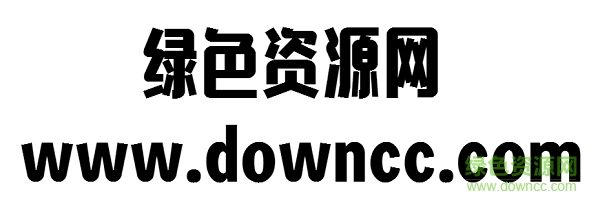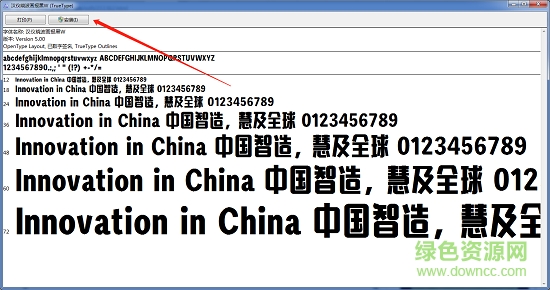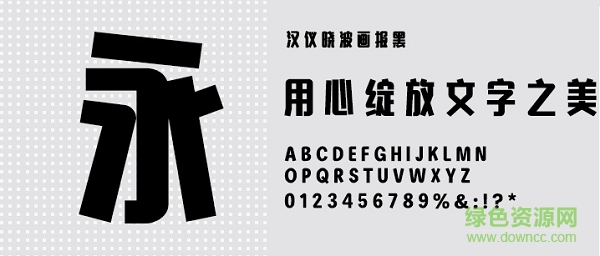
漢儀曉波畫報黑W(漢儀曉波藝術(shù)字體)是一款非常不錯的整體上瘦長的漢儀字體,正如其名畫報體,應(yīng)用于時尚雜志畫報的封面或是內(nèi)容都是不錯的選擇,彰顯時尚都市人群的無限魅力,字體轉(zhuǎn)角以圓滑的處理方式為主,更有一絲成熟穩(wěn)重的感覺,會給你不一樣的閱讀感受!
字體風(fēng)格: 古典 / 中國風(fēng) / 有趣 / 快樂 / 休閑 / 有力
推薦場景: 標(biāo)志 / 廣告 / 報紙 / 游戲 / 影視